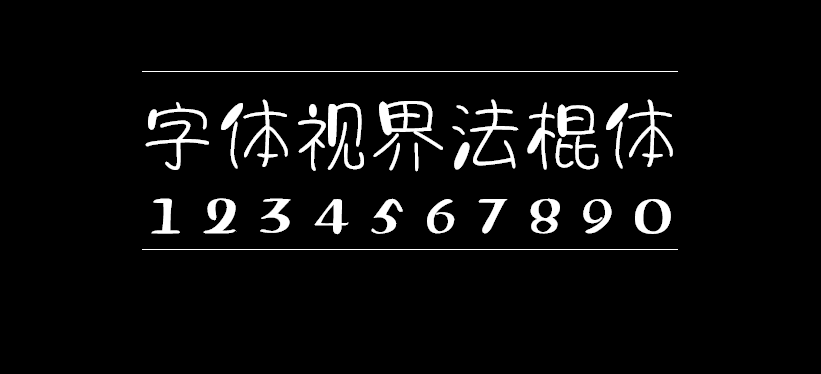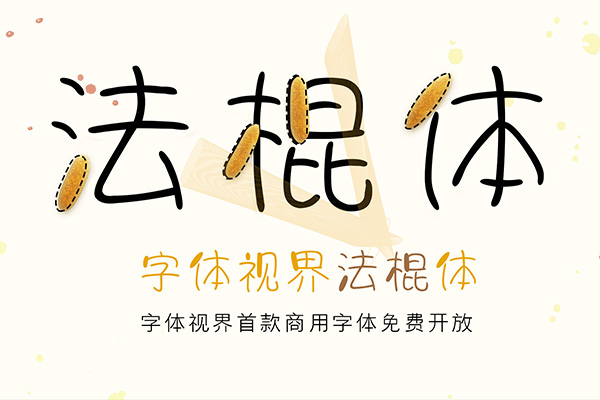
字体视界法棍体
字体视界法棍体由原字体(《义启嘟嘟体》登记号:沪作登字-2016-F-00712739)更名而来。由上海义启信息科技有限公司字库部员工通过字体软件进行设计与制作,为了让更多的人可以免费使用商用字体,公司决定改名为《字体视界法棍体》,并于2019年7月17日字体节这天在字体视界官网发布许可广大用户免费商用。
字体视界法棍体笔画中间呈弧形外拓,充满张力,加粗字形笔画显得更可爱个性;结构空间变化不像正体那样小,以拙为巧,憨态可掬。这款字体笔画充满张力,结构外圆内疏,左右呼应如手写,各个字生机勃勃又融为一体,整体一气呵成。